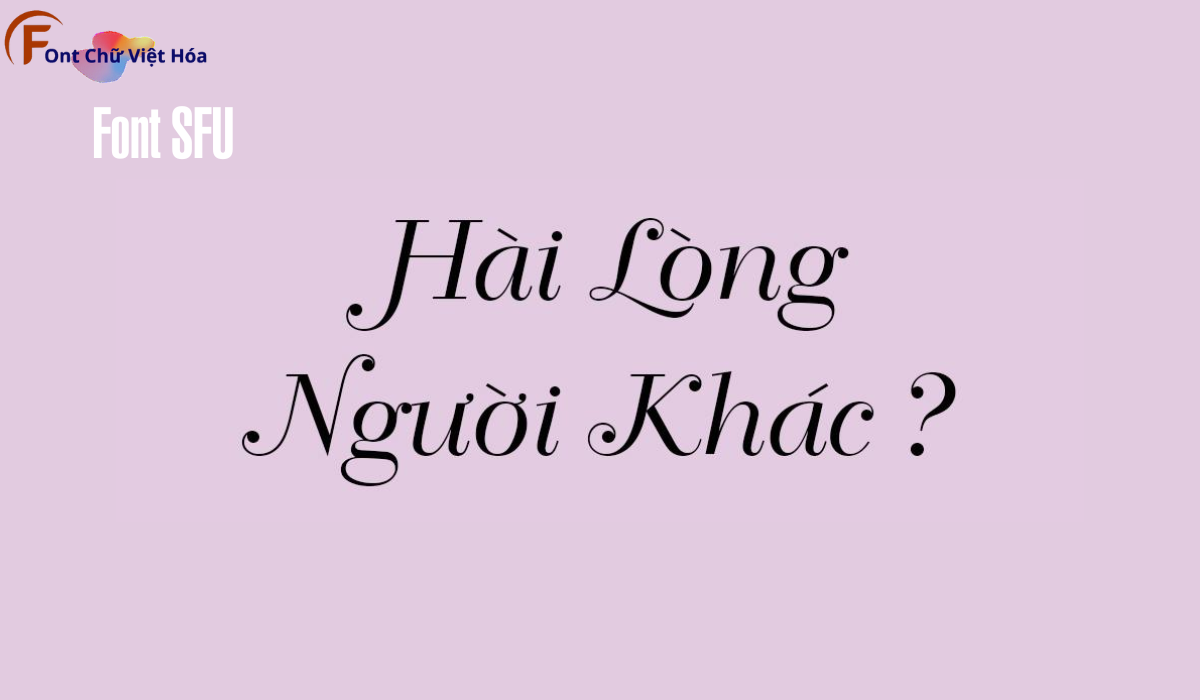
Font SFU Ariston Việt Hóa
Font SFU Ariston
Tác giả: SFU
Bộ Font: SFU
Phân loại: Cá tính
Kiểu chữ: Không chân
Độ dày: Regular, Bold
Font SFU Ariston
Font SFU Ariston Việt Hóa, thuộc bộ font SFU, là sự kết hợp hoàn hảo giữa tính hiện đại và sự tinh tế với phong cách sans-serif hiện đại. Font này được thiết kế nhằm mục tiêu tạo ra sự rõ ràng và dễ đọc, đặc biệt phù hợp cho các thiết kế như poster, logo, và tiêu đề. Đặc điểm hình dạng của SFU Ariston là các đường nét mạnh mẽ và tỷ lệ chữ cân đối, giúp tạo ấn tượng thị giác mạnh mẽ và tối ưu hóa không gian trong thiết kế. Font này cũng đã được Việt hóa, mang đến sự linh hoạt và tiện dụng cho các dự án thiết kế bằng tiếng Việt, giúp người dùng dễ dàng tiếp cận và sử dụng.
Font SFU Ariston việt hóa Font chữ SFU Ariston
SFU Ariston font character map